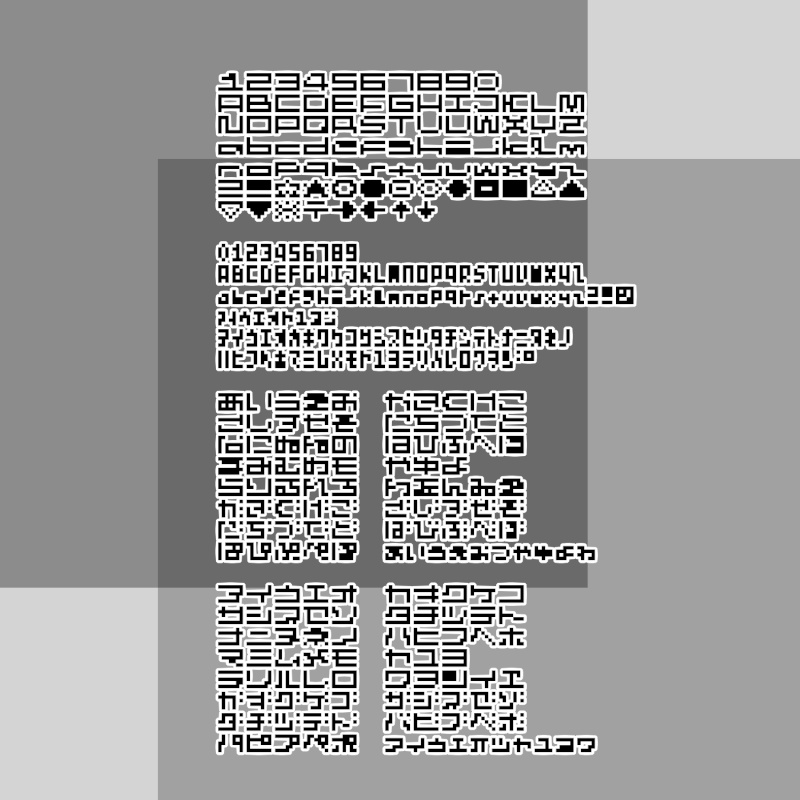
フリーフォント「カクガクネメス」(無料・商用可)
「カクガクネメス(Qma-kakugakunemes.ttf)」は フォント作成について何も知らない触手(加熱九真/shokushuQ)が https://www.pentacom.jp/pentacom/bitfontmaker2/ さんの力によって、手打ちしてつくったドットのフォントです。 何も知らないので横書きのことしか考えていません。 ■利用範囲 個人利用、商用利用、ウェブフォントやゲームなど独自性のあるコンテンツへの組み込みは自由です。 年齢制限が必要なコンテンツにもご使用頂けます。 ■禁止事項 犯罪行為や違法行為への使用、改変前のフォントファイルを単独で再配布することは禁止します。 商標登録など、第三者が本フォントを使用できなくなる行為は禁止します。 ■改変と再配布 収録文字の8割以上を改変し、本規約(readme.txt)を改変前フォントの規約として明記・同梱することで再配布可能です。 ■免責 本フォントの使用により生じた損害について、制作者(加熱九真/shokushuQ)は一切の責任を負いません。 ■その他 必須ではありませんが、使用の際にクレジット記載があると嬉しいです。 ■収録文字について 全角スペースはかなり中途半端な幅です(修正方法模索中) 半角スペースを1ピクセル分にしてあるので、それでうまく調整してください。 ■全角 1234567890 ABCDEFGHIJKLMNOPQRSTUVWXYZ abcdefghijklmnopqrstuvwxyz ?!☆★○●◎◇◆□■△▲▽▼※〒→←↑↓ ■半角 0123456789 ABCDEFGHIJKLMNOPQRSTUVWXYZ abcdefghijklmnopqrstuvwxyz?!@ ァィゥェォャュョッ アイウエオカキクケコサシスセソタチツテトナニヌネノ ハヒフヘホマミムメモヤユヨラリルレロワヲン゙゚ ■ひらがな あいうえお かきくけこ さしすせそ たちつてと なにぬねの はひふへほ まみむめも やゆよ らりるれろ わをんゐゑ がぎぐげご ざじずぜぞ だぢづでど ばびぶべぼ ぱぴぷぺぽ ぁぃぅぇぉ っゃゅょゎ ■カタカナ アイウエオ カキクケコ サシスセソ タチツテト ナニヌネノ ハヒフヘホ マミムメモ ヤユヨ ラリルレロ ワヲンイヱ ガギグゲゴ ザジズゼゾ ダヂヅデド バビブベボ パピプペポ ァィゥェォ ッャュョヮ ____________________________ 20250404、規約変更。